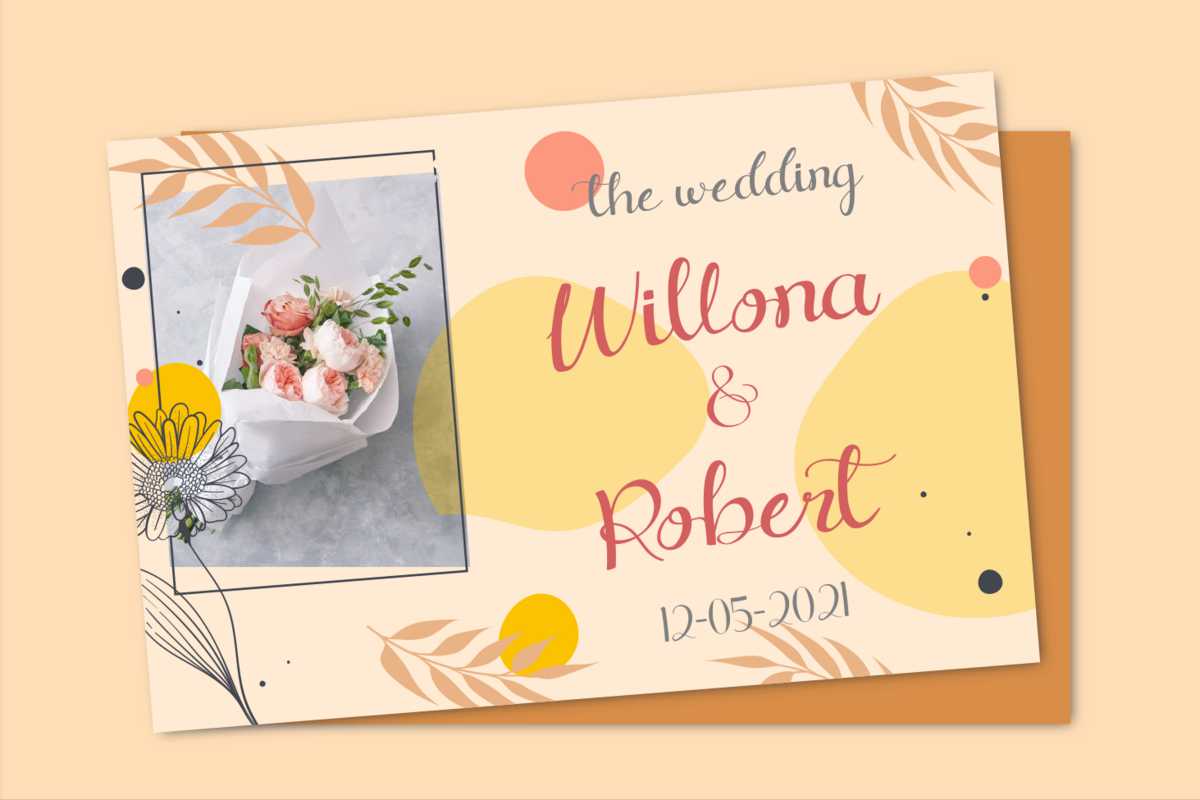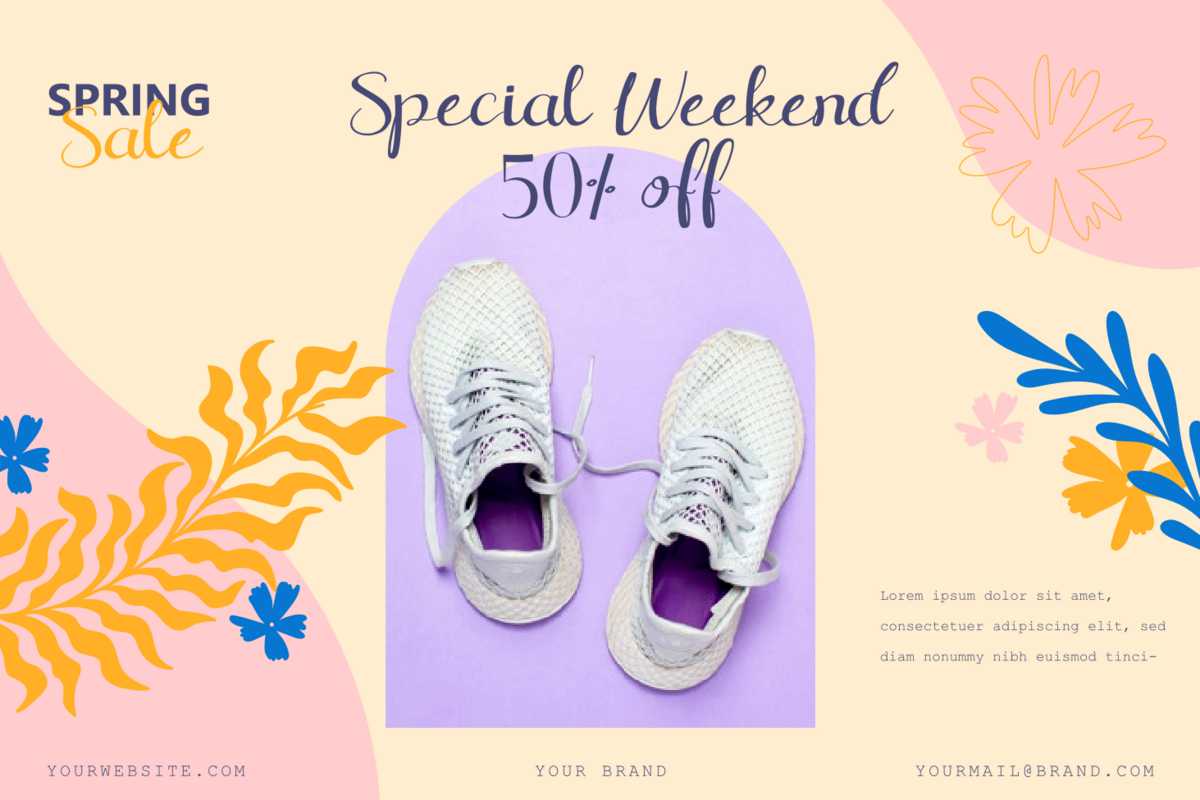
Belvinacalligraphyfont是一种现代的书法,美丽而浪漫的剪贴画。它的特点是具有立体感、结扎和擦洗。这种字体美丽而优雅,非常适合于书写项目,如增加灵感、美化运动艺术、吸引眼球的社会主题、引文、剪贴画和更多。Belvinacalligraphyfont是一种现代书法,美丽和浪漫的彩绘字体。它的特点是立体感、连字和涂鸦。这种字体美丽而优雅,非常适合于书写项目,如增加灵感、美化艺术、吸引眼球的社交主题、引用、剪贴画等等。